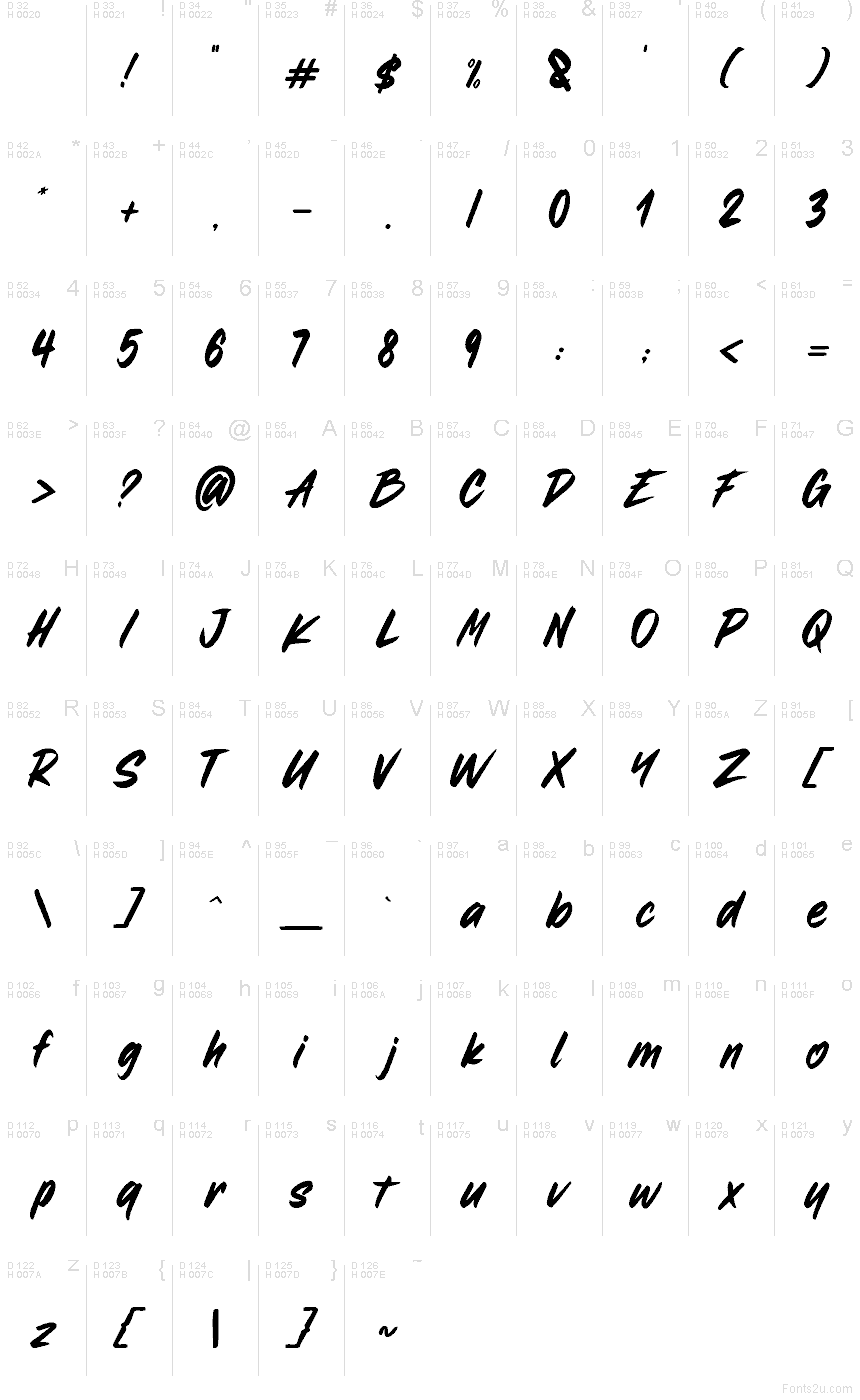
The Blue Wave di BlackFridayFont è un font brush script gratuito con una inclinazione veloce e "surfy", caratterizzato da tratti spessi che sembrano tracciati in un colpo solo. Le lettere sono fortemente inclinate e strettamente collegate, con inizi appuntiti, occhielli arrotondati e una finitura slanciata che conferisce all'intero font un'atmosfera rilassata, tipica dei vecchi cartelloni sbiaditi dal sole.
È ideale per il branding di negozi sulla spiaggia, etichette di bevande, titoli di poster, volantini di eventi e packaging informali dove serve quel tocco grafico manuscritto. Come font gratuito, funziona bene anche per copertine, grafiche per i social e titoli brevi, specialmente quando vuoi che il ritmo del pennello largo dia carattere alla parola.